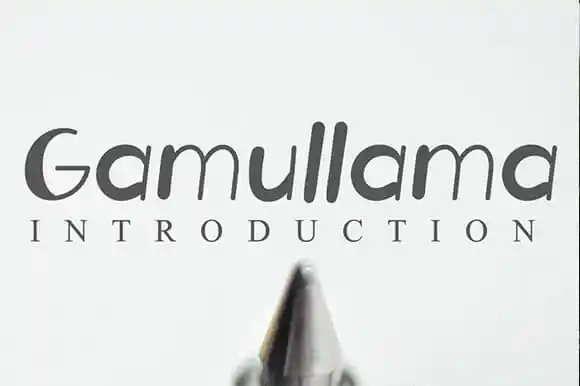
Gamullama Displays Font – Download Grátis
A Gamullama Displays Font é uma opção perfeita para projetos que precisam de um toque autêntico e sofisticado. Ela foi criada com a intenção de se destacar tanto nas superfícies como nos pequenos detalhes, oferecendo letras atemporais para uso em muitas categorias, desde identidades digitais até embalagens de produtos. Seja um anúncio publicitário, uma caixa de produto ou mesmo um logotipo social de casamento, a Gamullama Displays Font traz uma personalidade única e elegante. Seu designer atencioso e artístico, andikastudio, sabe exatamente como criar elementos que se destacam em qualquer situação. Este projeto de fonte inclui um amplo leque de opções para os profissionais de design, garantindo uma experiência visual atraente e sofisticada. Inspirado em estilos antigos e atemporais, a Gamullama Displays Font é perfeita para aquelas criações que exigem mais do que apenas bom gosto. É ideal para qualquer projeto que exige um toque de delicadeza em suas mensagens visuais.